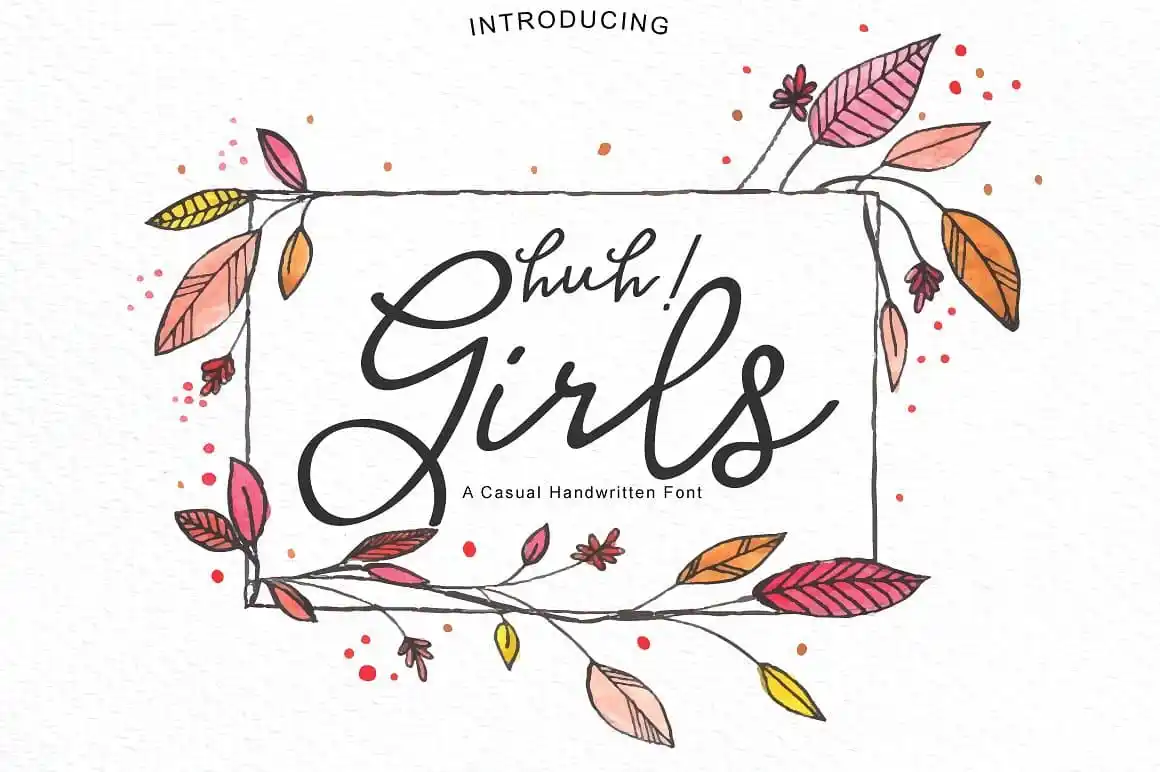
Introduzimos Huh! Girls! É uma fonte premium criada pela Nursery Art, disponível na CreativeMarket. Agora, é gratuita para download hoje. Esta fonte casual, com traços a esmaecer e diversas variações de letras, oferece infinitas possibilidades para projetos pessoais ou profissionais. Perfeita tanto para inviáveis casuais quanto para blogs pessoais, Huh! Girls também pode ser usada para criar logomarcas, frames decorativos para a casa ou mesmo capas de livros e materiais de estação para o seu negócio pequeno ou até mesmo para revistas. Com sua facilidade na criação de designs únicos e perfeitos, Huh! Girls é um recurso gráfico incrível que pode enriquecer qualquer projeto. Sem dúvida, esta fonte se destaca como uma opção versátil em um ambiente digital cheio de personalização.